モダンなひねりを加えてメモリレーンを旅する準備はできていますか? Typewriterフォントは、古い学校のライティングの魅力をデジタル時代にもたらし、Google Docsにはこれらのレトロな宝石の隠れ家があります。この記事では、Googleドキュメントの最高のタイプライターフォントをご覧ください。クラシックなタッチでドキュメントを際立たせます。ヴィンテージをテーマにした招待状を作成したり、履歴書に独特のエッジを与える場合でも、フォントが待っています。
この記事を読み終えた後、Googleドキュメントで使用するトップタイプライターフォントがわかります。プロジェクトに合ったフォントを決定するのに役立つ長所と短所が装備され、タイポグラフィの冒険を強化するための追加のヒントがあります。飛び込みましょう!
導入
キーのリズミカルな音が鳴り響き、ラインの端に鐘が鳴ること、新鮮な紙の中で転がる触覚の満足度を想像してください。タイプライターのフォントのおかげで、それがタイプライターの世界であり、完全に失われていない世界です。これらのフォントは、私たちのプレーンデジタルドキュメントに懐かしさと個性を少しもたらします。彼らは、すべての印刷された言葉が愛の物理的な労働であった時代を思い出させます。
Googleドキュメント用のTypewriterフォントについて話しているのはなぜですか?まあ、彼らは見た目だけではありません。彼らはあなたの文書を個人的な感じにさせ、標準的なアリアルと時代の新しいローマの海で際立っています。彼らは特に作家、デザイナー、そして彼らの作品にビンテージの魅力のタッチを追加したい人に関連しています。 Typewriterフォントは、深刻さ、気まぐれ、または過去のヒントを伝えることができます。だから、あなたがあなたの次のGoogleドキュメントを盛り上げたいなら、読んでください!
何を期待するか
次のリストでは、Googleドキュメントで利用できる最高のタイプライターフォントのいくつかを紹介します。各フォントのユニークなスタイルと、それがドキュメントにぴったりの理由について学びます。
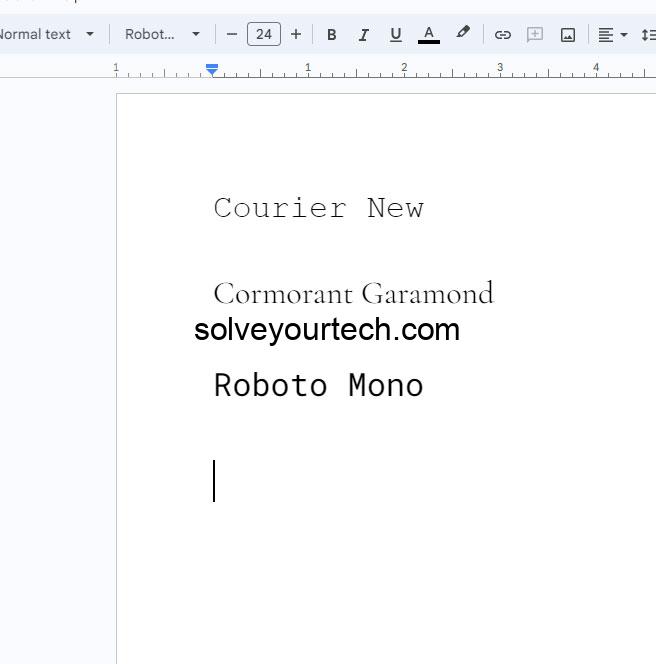
Courier New
典型的なタイプライターフォント。 Courier Newは、タイプライターフォントの小さな黒いドレスのようなものです。このモノラッチの宝石は、実際のタイプライターの出力を模倣する清潔で均一な外観のおかげで、書面、コーディング、デザインの定番でした。
Cormorant Garamond
エレガントで時代を超越した、ひねりを加えています。古典的なタイプライターフォントではありませんが、Cormorant Garamondは、ドキュメントに洗練されたタッチを追加できるビンテージの雰囲気を放ちます。モダンなフォントのアクセシビリティと古いスタイルのクラスのブレンドが必要な場合に最適です。
ロボットのお金
タイプライタースタイルのモダンなテイク。 Roboto Monoは、Typewriterフォントのモノスパースの魅力を取り、現代的なひねりを加えます。洗練されたラインと読みやすいフォームを備えたもので、レトロにならずにタイプライターの美学のヒントを望んでいる人には最適です。
長所
GoogleドキュメントのTypewriterフォントには、さまざまな方法でドキュメントを強化できるいくつかの利点があります。
文字を追加します
あなたの仕事に個性を注入してください。タイプライターフォントを使用すると、ドキュメント文字が即座に表示される可能性があります。それは典型的なフォントの選択から際立っており、読者が慎重に作成されたものを見ているように感じさせることができます。
読みやすさを向上させます
あなたのテキストを際立たせます。 Typewriterフォントはしばしばモノスパースであるため、ドキュメントの読みやすさを向上させることができます。各キャラクターは同じ量のスペースを占有し、目で簡単になり、長い読み取りに最適です。
ノスタルジア因子
過去の感覚をもたらします。タイプライターフォントは懐かしさを呼び起こし、読者を別の時代に戻します。これは、特定のテーマやストーリーテリングのテクニックに特に効果的です。
短所
タイプライターフォントには利点がありますが、制限もあります。
使いすぎることができます
良いことが多すぎます。 Typewriterフォントは魅力的ですが、それらを過度にまたは不適切に使用すると、ドキュメントを専門的または真剣に受け止めるのが難しくなります。
常にプロフェッショナルではありません
正式な文書には適していない場合があります。ビジネスまたは正式な学術文書の場合、TypewRiterフォントは正しいトーンを伝えることはできません。あなたがそれらを使用しているコンテキストを考慮することが重要です。
限られた可用性
すべてのタイプライターフォントが利用できるわけではありません。 Google Docsにはまともなフォントの選択がありますが、探しているすべてのタイプライターフォントがあるとは限りません。これにより、特定の外観を念頭に置いている場合、選択肢を制限できます。
追加情報
Google DocsでTypewRiterフォントを使用する場合、もう少し留意してください。すべてのプロジェクトがタイプライターフォントに適しているわけではありません。彼らは、創造的な執筆、テーマパーティーの招待状、または過ぎ去った時代を呼び起こしたいプロジェクトに最適です。これらのフォントを効果的に使用するための鍵は、緩和とコンテキストであることを忘れないでください。タイプライターフォントのドキュメント全体が過剰になる可能性がありますが、ヘッダーまたはタイトルにそれを使用すると、適切な量の古い学校の才能が追加されます。
別のヒントは、タイプライターフォントと適切な画像を組み合わせることです。たとえば、ビンテージコンサートのポスターを作成している場合、タイプライターフォントとレトロ設計の要素を組み合わせることで、プロジェクトをポップにすることができます。また、さまざまなデバイスの読みやすさを検討してください。デスクトップで見栄えが良いものは、モバイル画面ではうまく翻訳されない可能性があるため、さまざまなプラットフォームでテストしてください。
まとめ
よくある質問
Typewriterフォントは履歴書に適していますか?
それはあなたが申請している仕事に依存します。クリエイティブ産業は独自性を高く評価するかもしれませんが、伝統的な分野はおそらくそうではありません。
TypewRiterフォントはメインテキスト本体に使用できますか?
はい、しかし、読みやすさのために、見出しやタイトルに使用する方が良いことがよくあります。
結論
Typewriterフォントは、過去のうなずきだけではありません。彼らは、デジタル作品に個性と懐かしさを加えたいクリエイターのためのツールです。テーマのイベント、個人的なプロジェクトであろうと、履歴書の山で目立つ場合でも、これらのフォントはその特別な何かを提供できます。それらを賢く使用することを忘れないでください。
昨年のタイプライターと同様に、これらのフォントは思慮深いタッチで使用するのが最適です。この記事の洞察を使用して、次のGoogleドキュメントでTypewRiterフォントの探索と実験を開始する準備ができています。幸せなタイピング!